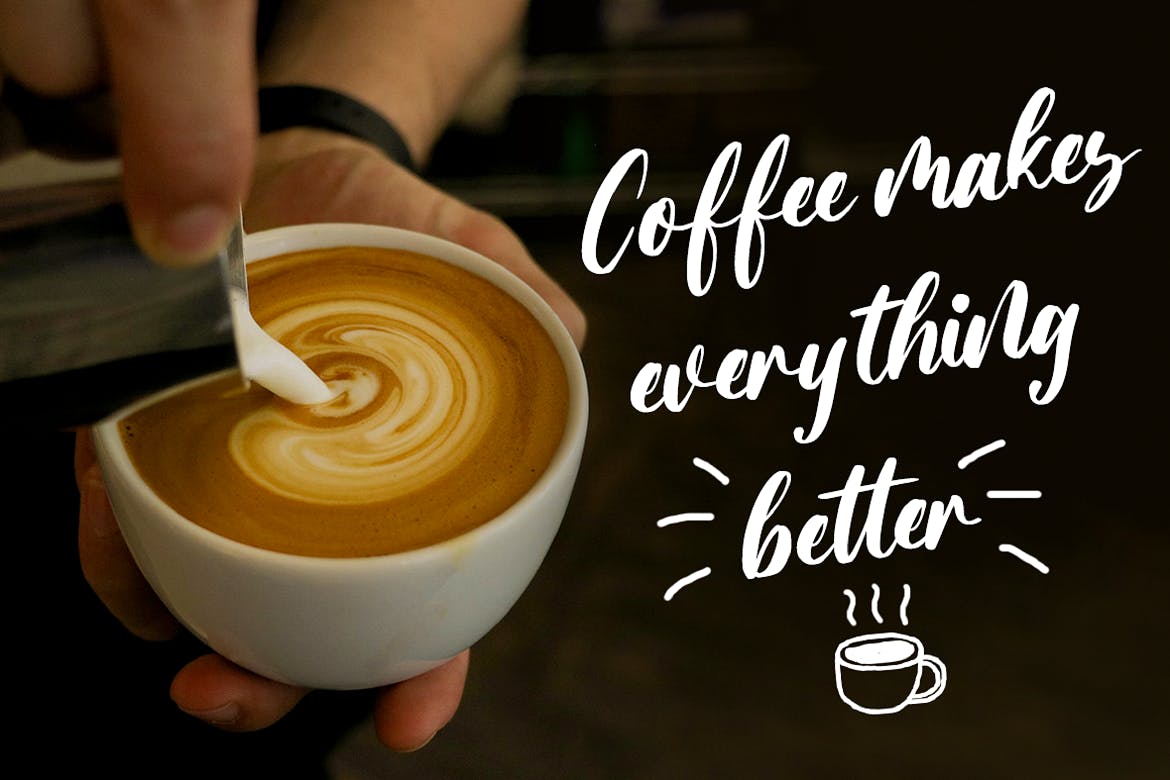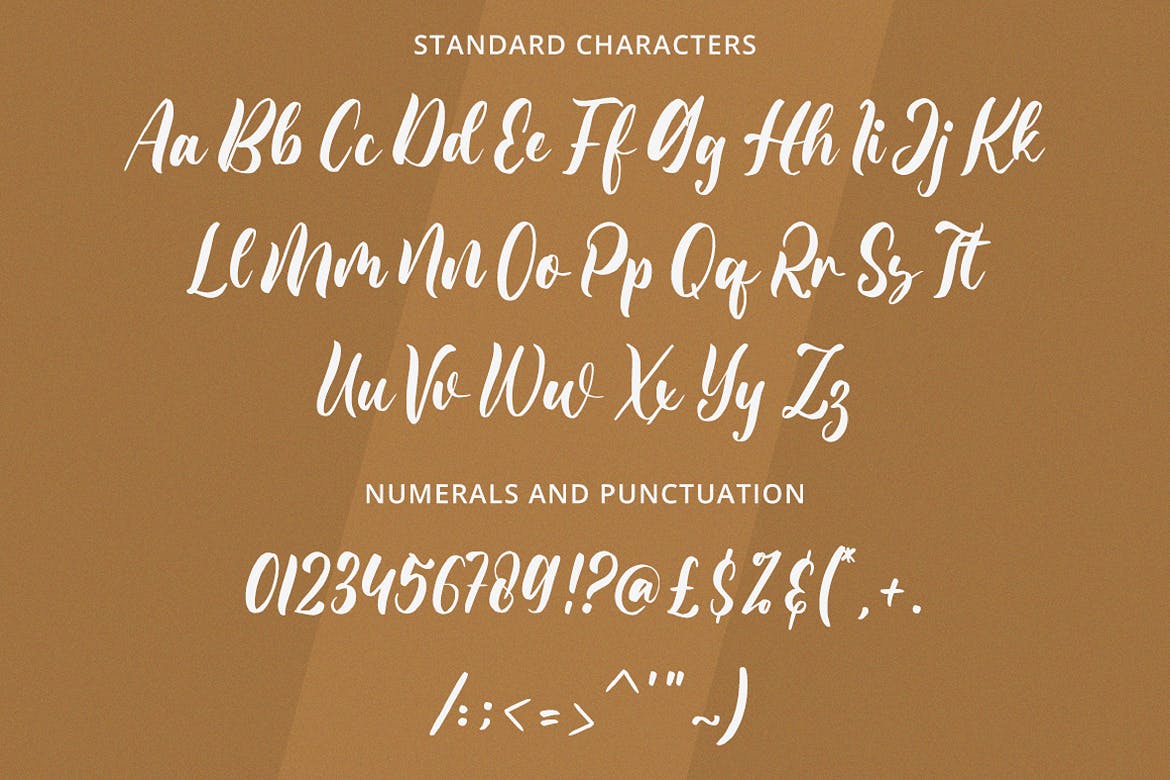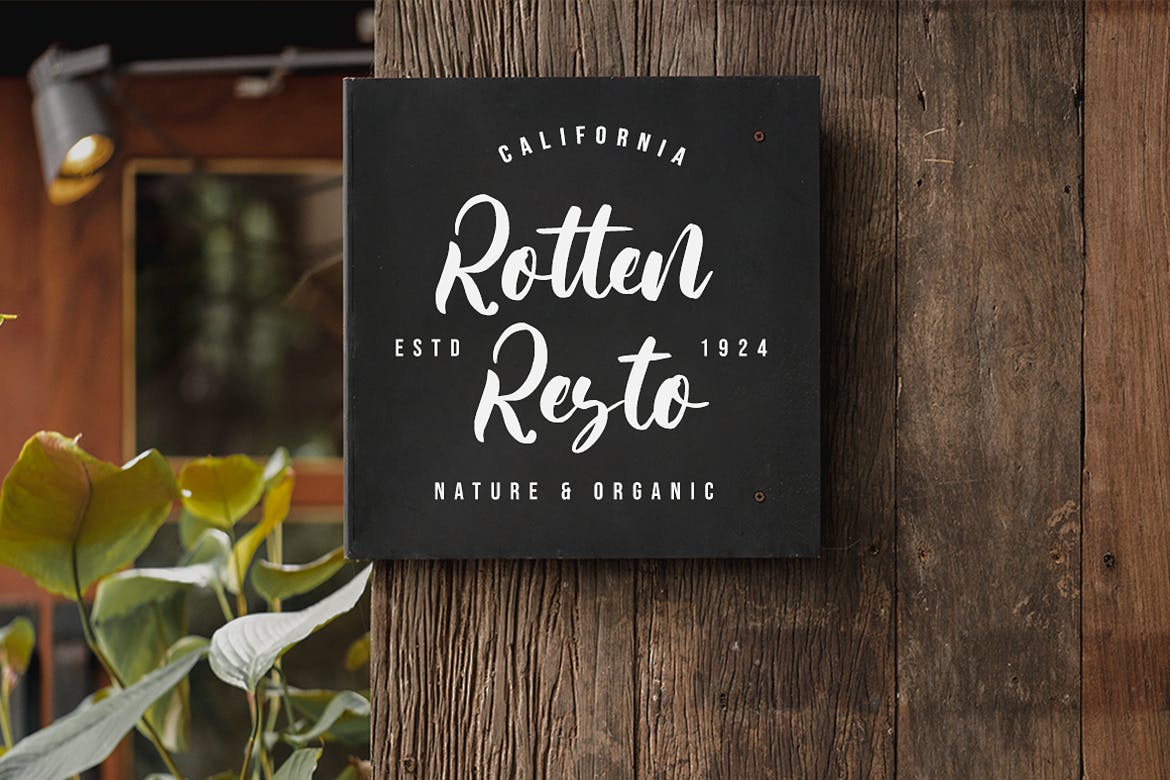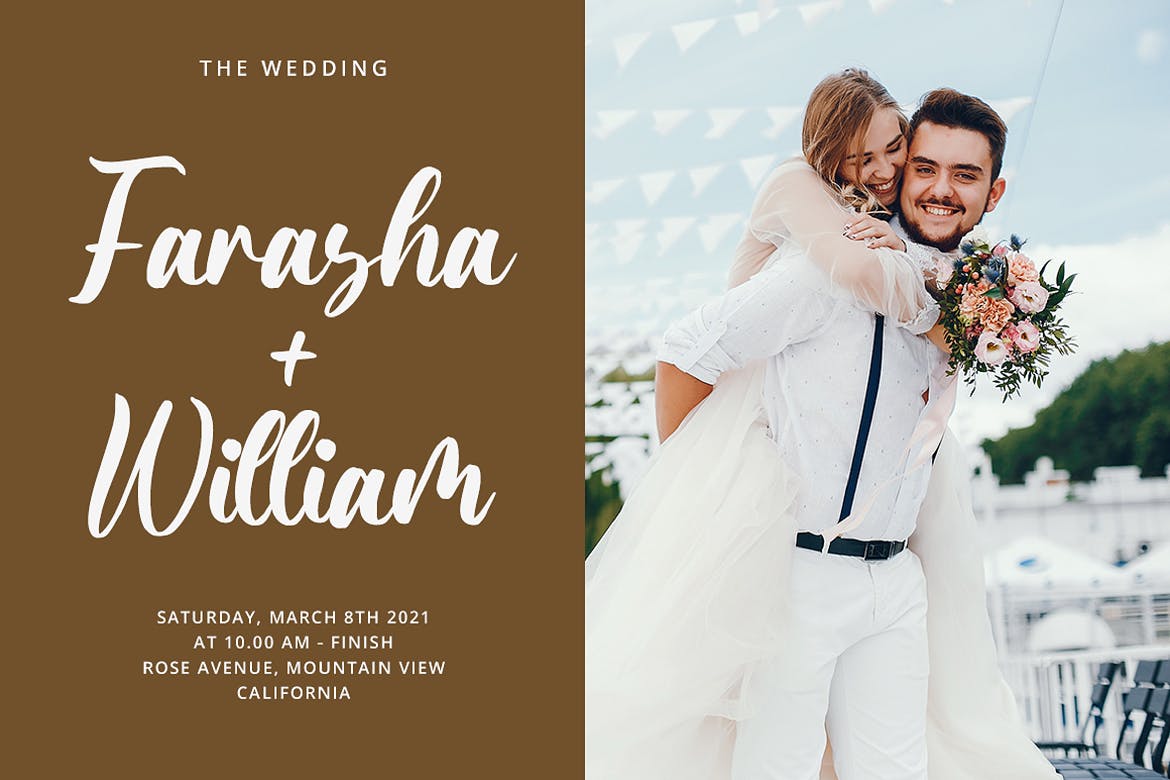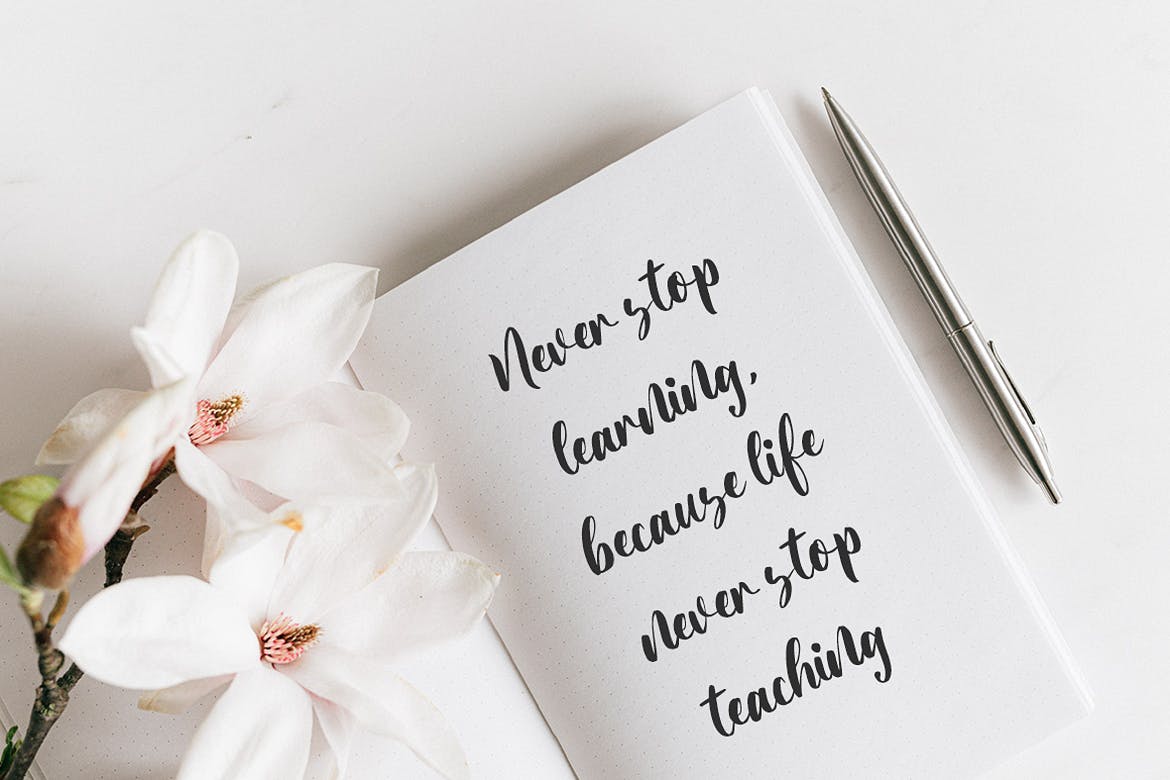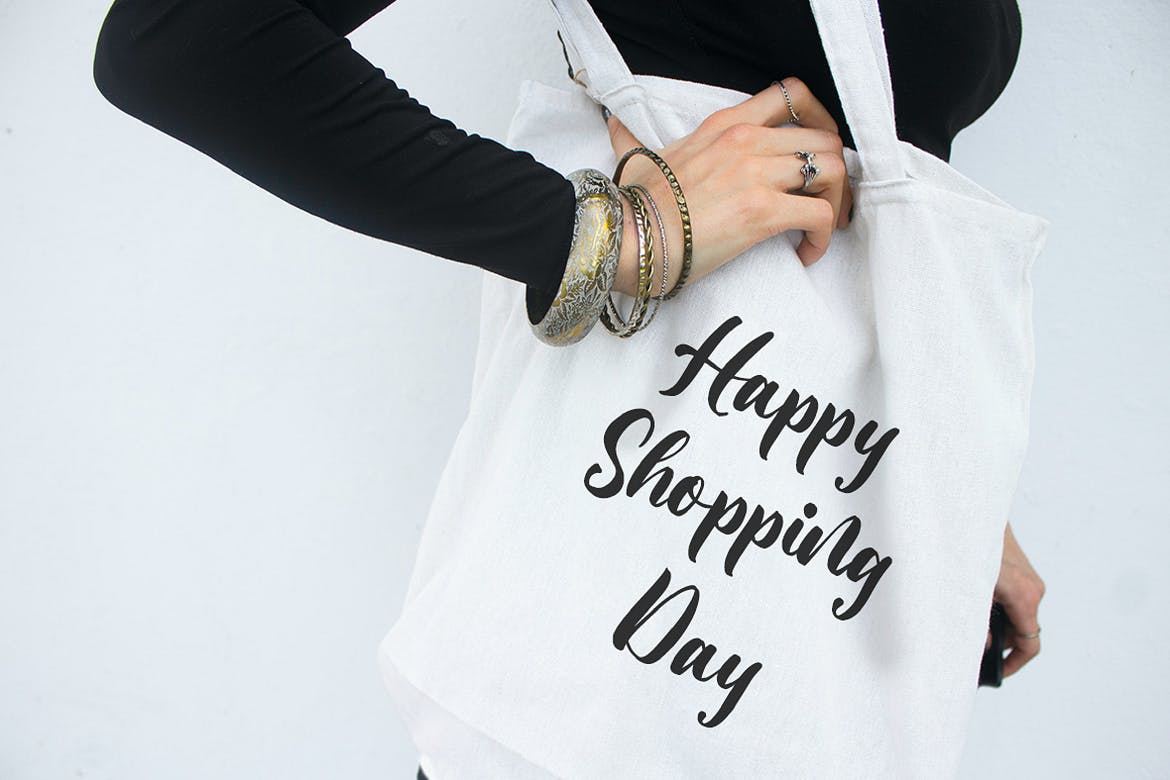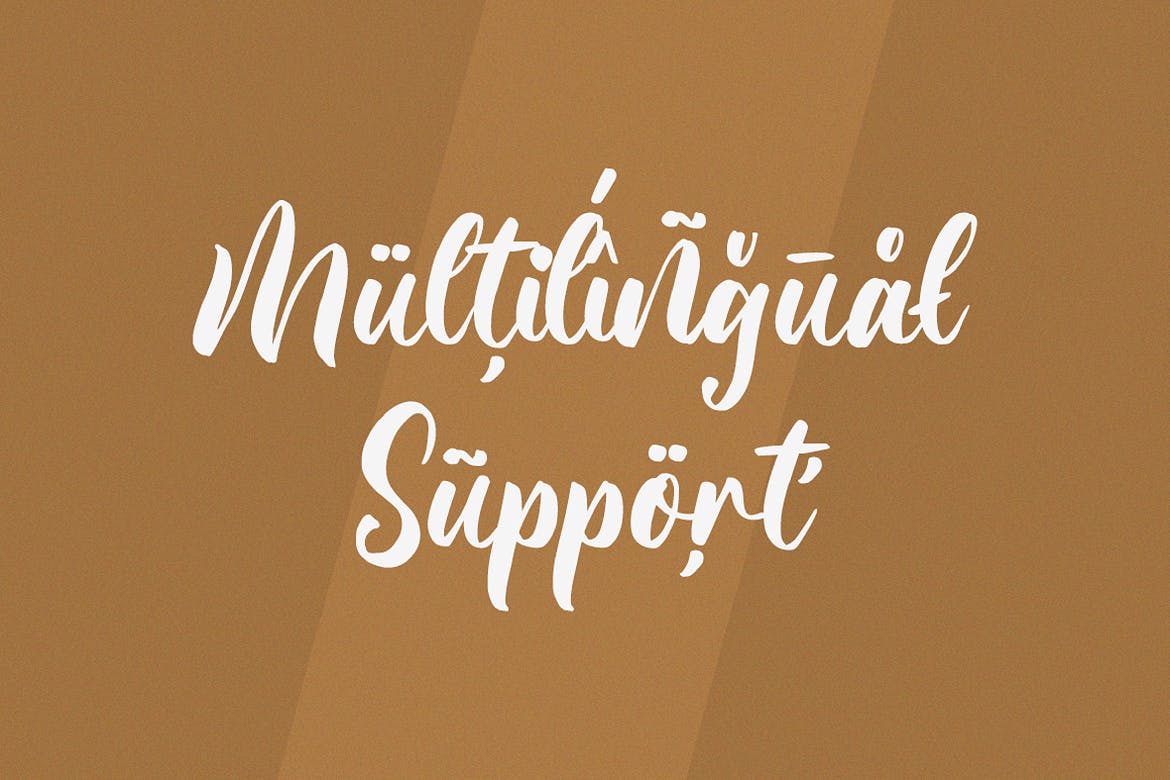
فونت Butterie یک فونت خوشنویسی مدرن است که با ترکیبی از حس مدرن و کلاسیک طراحی شده است. این فونت برای وبسایتهای شیک، برندینگ در شبکههای اجتماعی، بنرهای پینترست، دعوتنامههای چاپی و موارد دیگر ضروری است!
فونت خوشنویسی Butterie یک فونت بیزمان است که هرگز شما را در مقابل مخاطبان، مشتریان، مهمانان یا هر کسی که در اطرافتان است، ناامید نخواهد کرد!